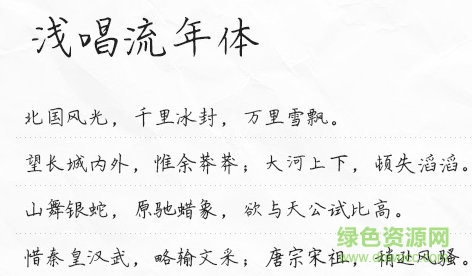
浅唱流年字体是一款思雨字库上线的清新别致的手写字体,字迹简洁而婉约,给人清新细腻的笔触和层次鲜明的结构感,让你的艺术设计更加质朴好看,喜欢的朋友就来绿色资源网试试吧!
“一川云水,一朵彼岸,流年于指尖散落;一影碎念,一场风花,浅吟低唱成曲。”——浅唱流年体。
本字体是在国家标准简体字库GB2312所包含6763汉字的基础上,又增加了近200常用字,已经覆盖了大陆99.75%的汉字使用频率,足以满足日常需求。
浅唱流年字体出自思雨字体,以手写体风格而闻名,字迹清晰有着极佳的辨识度,给文字更多的书写娟秀体验,让你的包装设计、平面设计更加随和、平易近人!